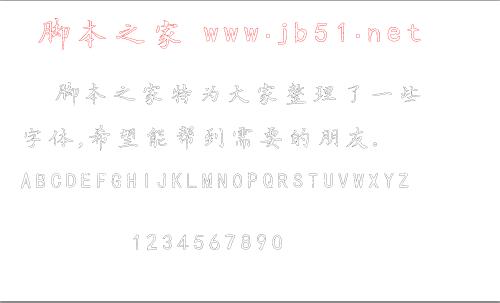
尖鋒楷書(shū)空心體運(yùn)用空心設(shè)計(jì),體現(xiàn)出有立體感,有質(zhì)感,在設(shè)計(jì)中應(yīng)用十分廣泛,適合應(yīng)用于藝術(shù)設(shè)計(jì)、平面宣傳設(shè)計(jì)、網(wǎng)頁(yè)設(shè)計(jì)、書(shū)法字體,海報(bào)設(shè)計(jì)等領(lǐng)域,歡迎喜歡這款字體的朋友下載收藏。